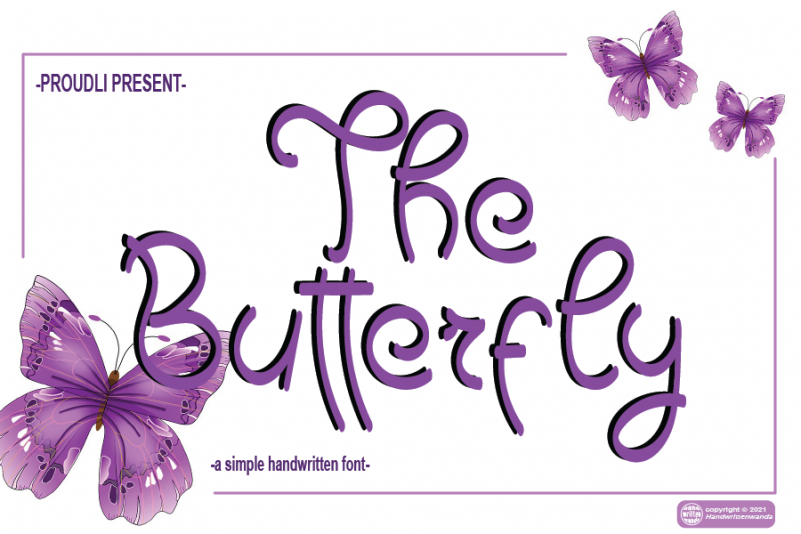
The Butterfly Font – Download Grátis
Esta é uma fonte escrita a mão, cheia de encanto e flexibilidade para projetos variados. Ela tem um toque quente e engraçado que transmite um senso de alegria, tornando cada ideia de projeto realista e única. Se você adora o estilo da Butterfly Font, esta é uma excelente escolha. É perfeita tanto para uso pessoal quanto profissional, pois pode ser adaptada em inúmeras variações. Aproveite suas habilidades criativas com essa bela fonte escrita a mão.